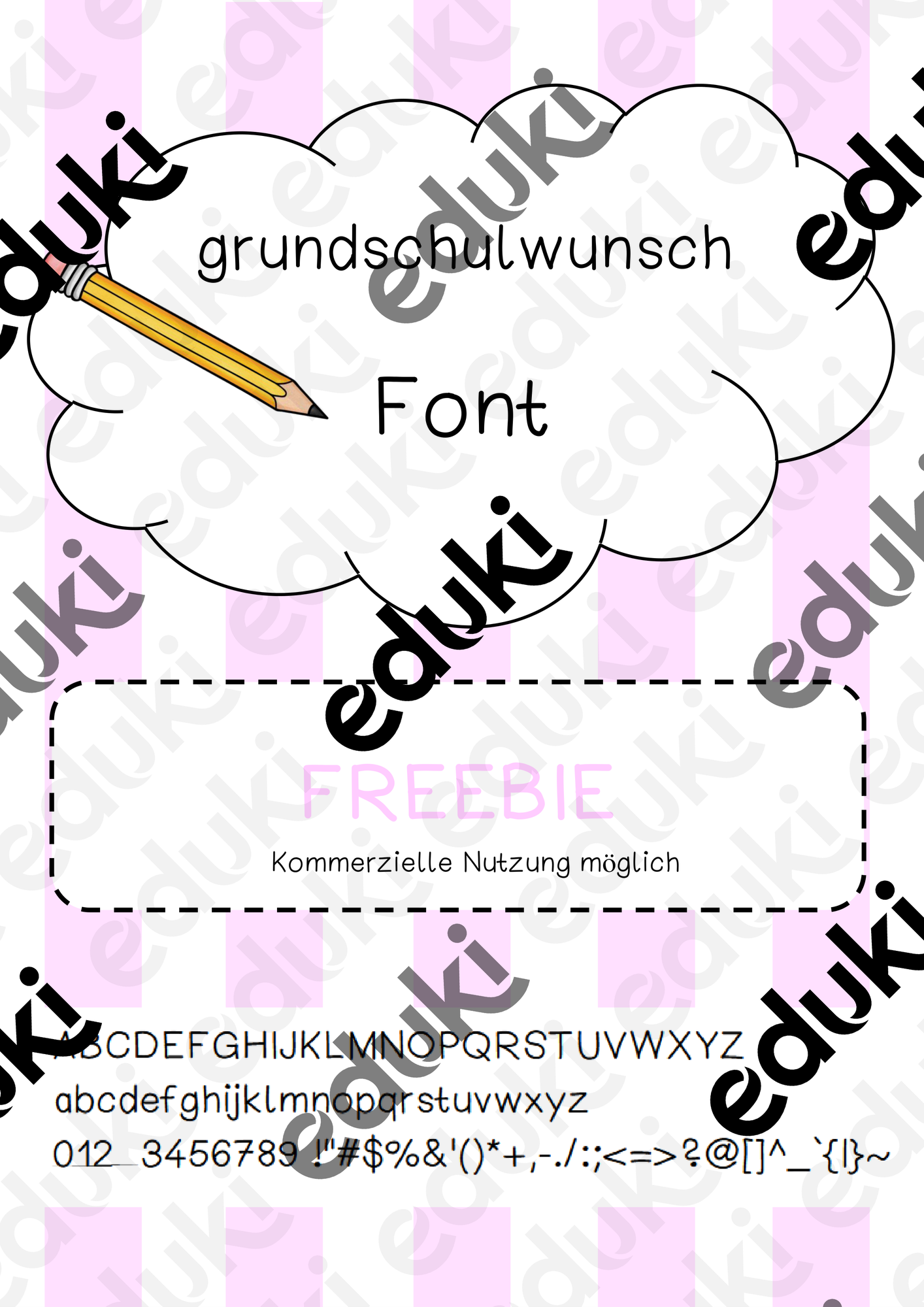
In meiner Schulzeit wurde ich für meine Schriftart immer gelobt :) Und auch heute werde ich oft gefragt, ob ich etwas an die Tafel oder auf ein Plakat schreiben kann.
Darum habe ich meine Schriftart digitalisiert :)
Ich liebe diese Schrift! Sie ist perfekt für Wortkartenmaterial, was an der Tafel hängen soll und ist auch von LRS-Schülern gut lesbar. Vielen Dank fürs kostenlose zur Verfügung stellen! :-)
Die Schrift ist wirklich total schön und sehr leserlich! Danke :-)
Die Schrift ist einfach super!Sehr klar und deutlich.
Eine so schöne Schrift! Leider sind die "Gänsefüßchen unten" nicht mit dabei. Lasst sich das noch ergänzen? Liebe Grüße!